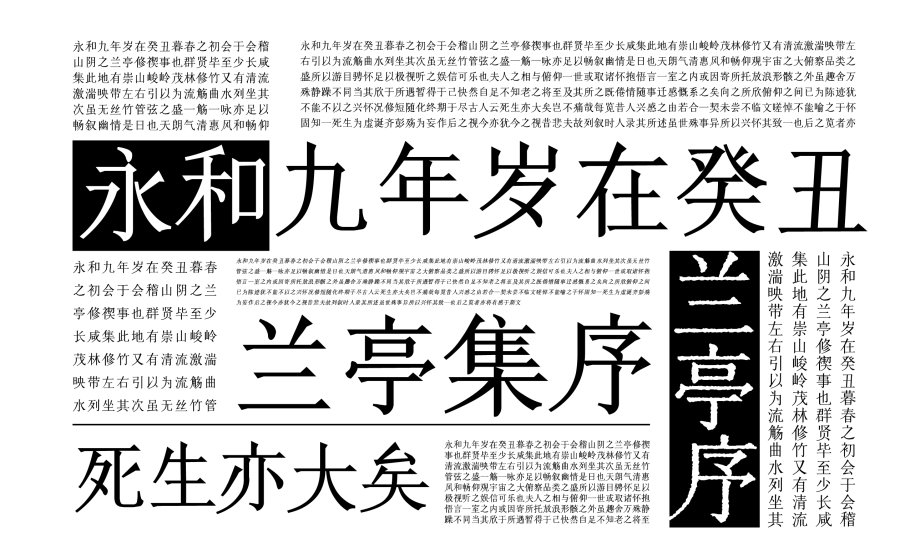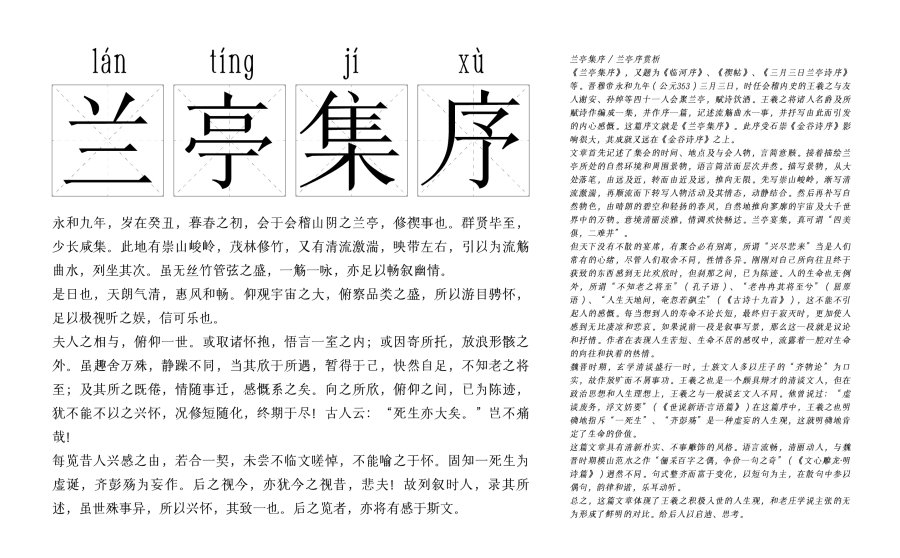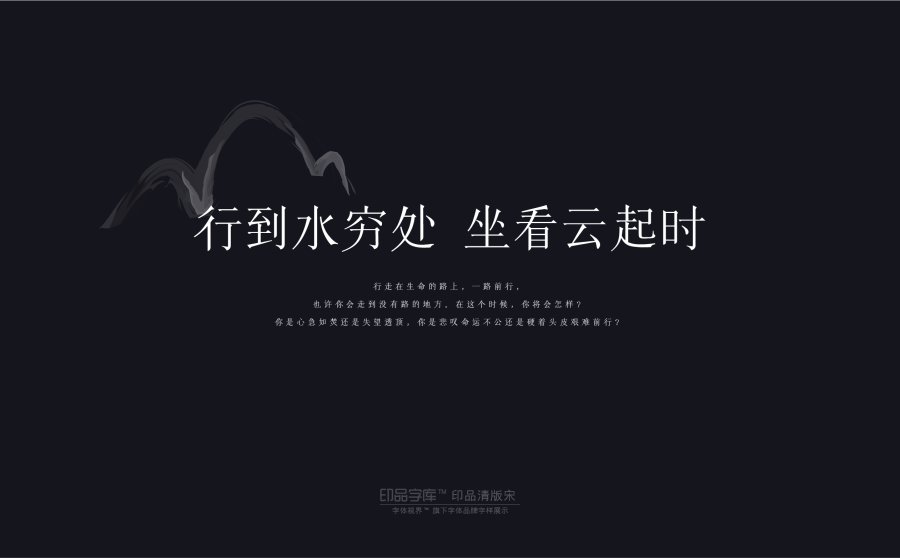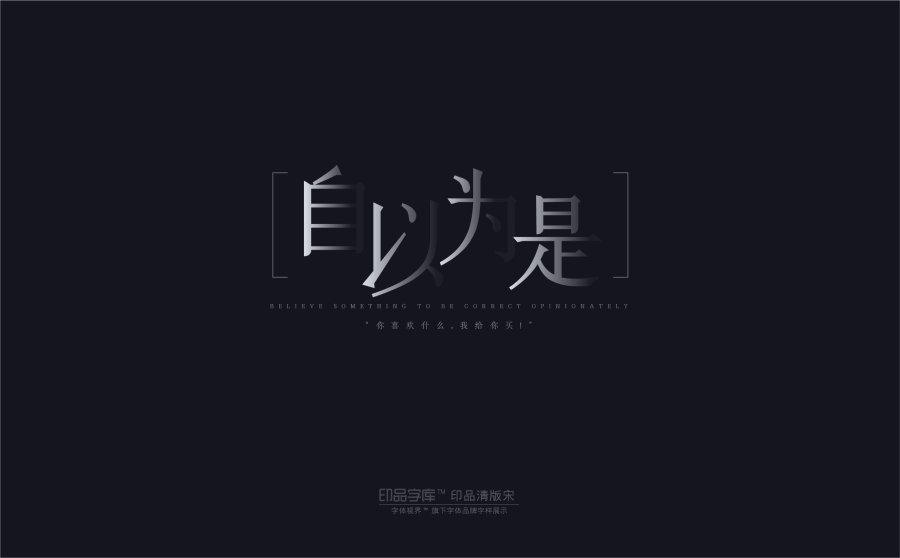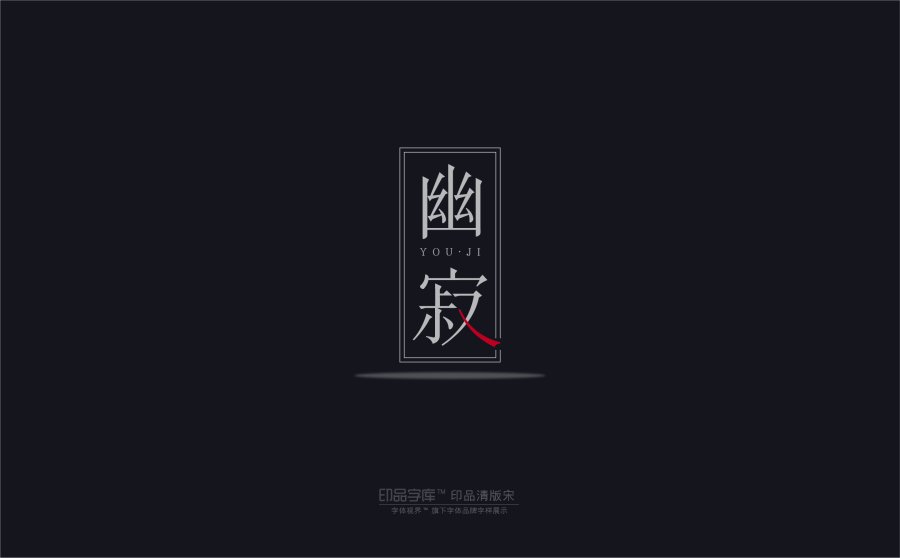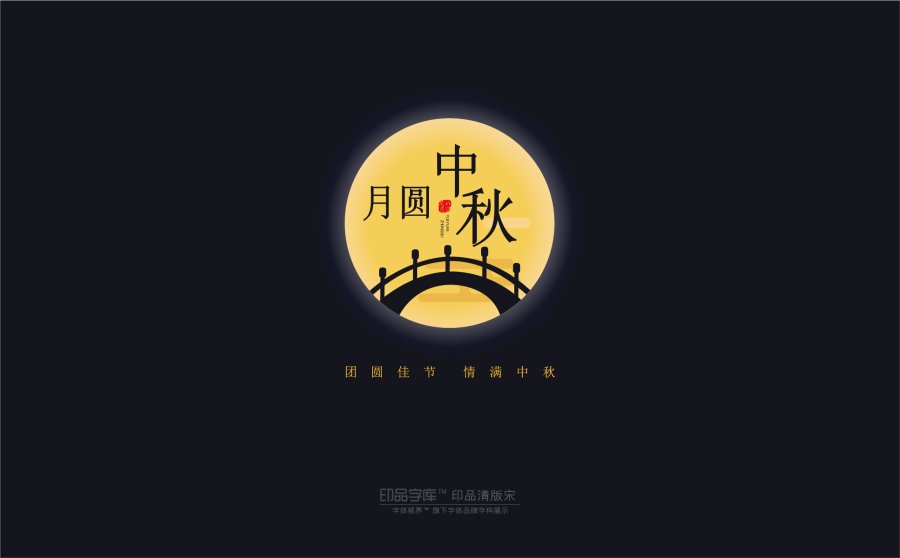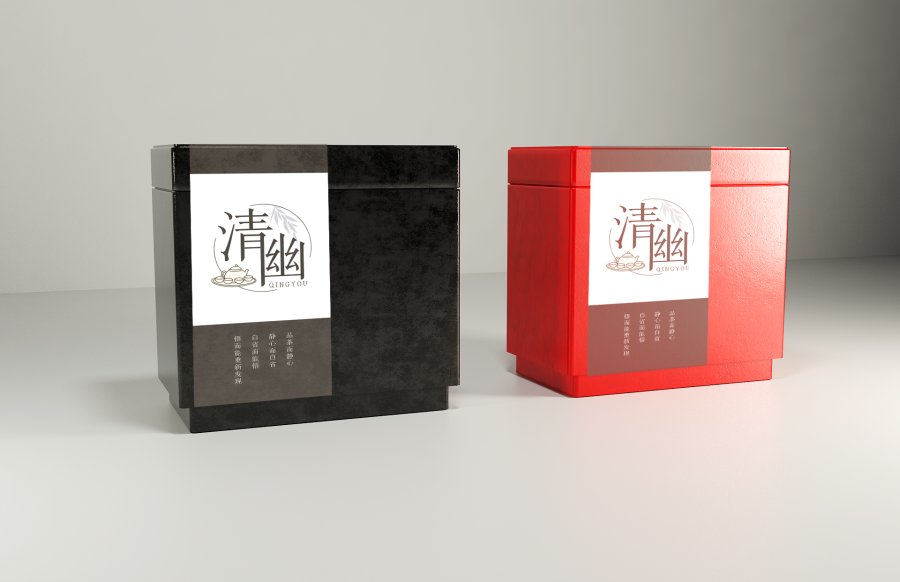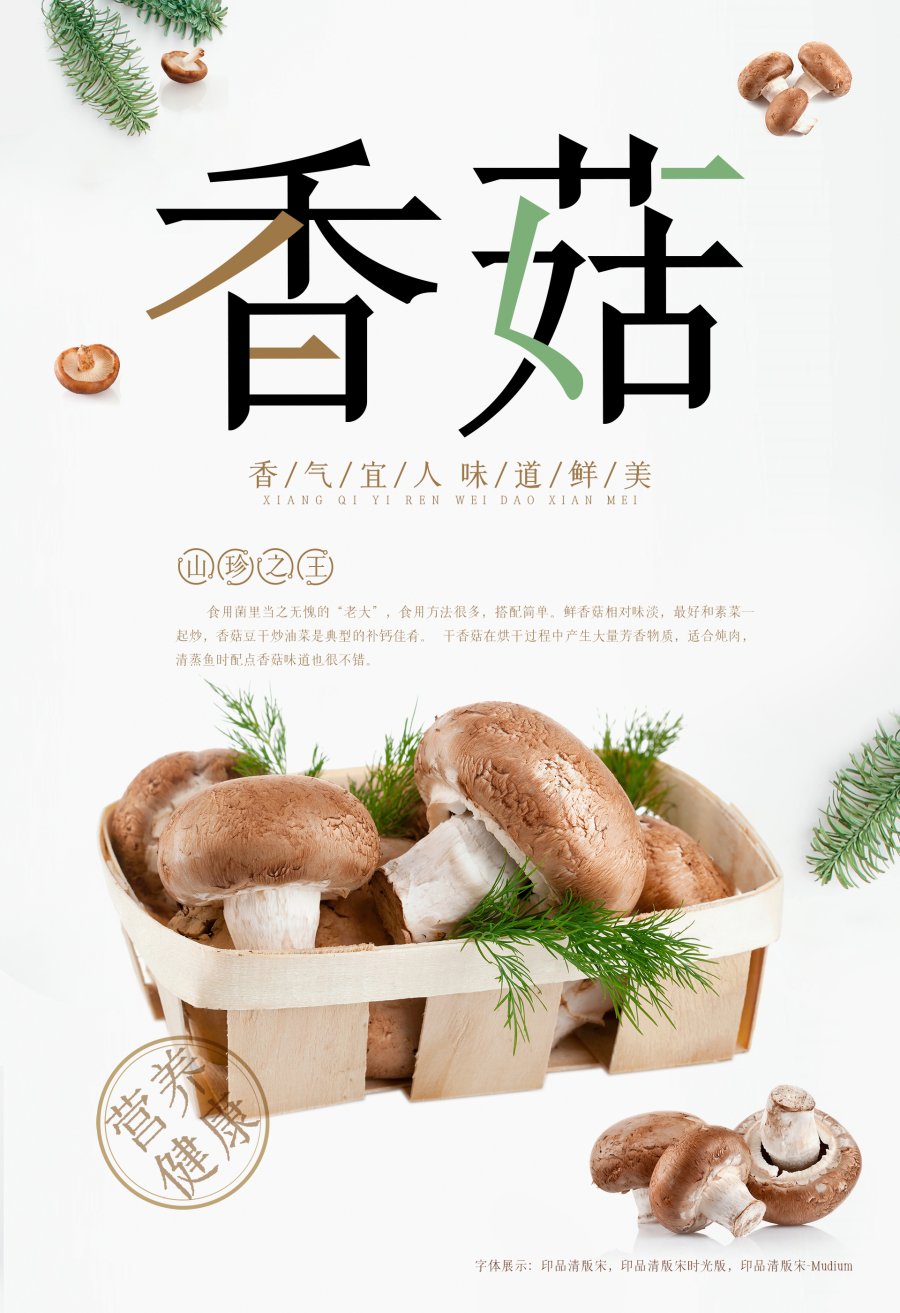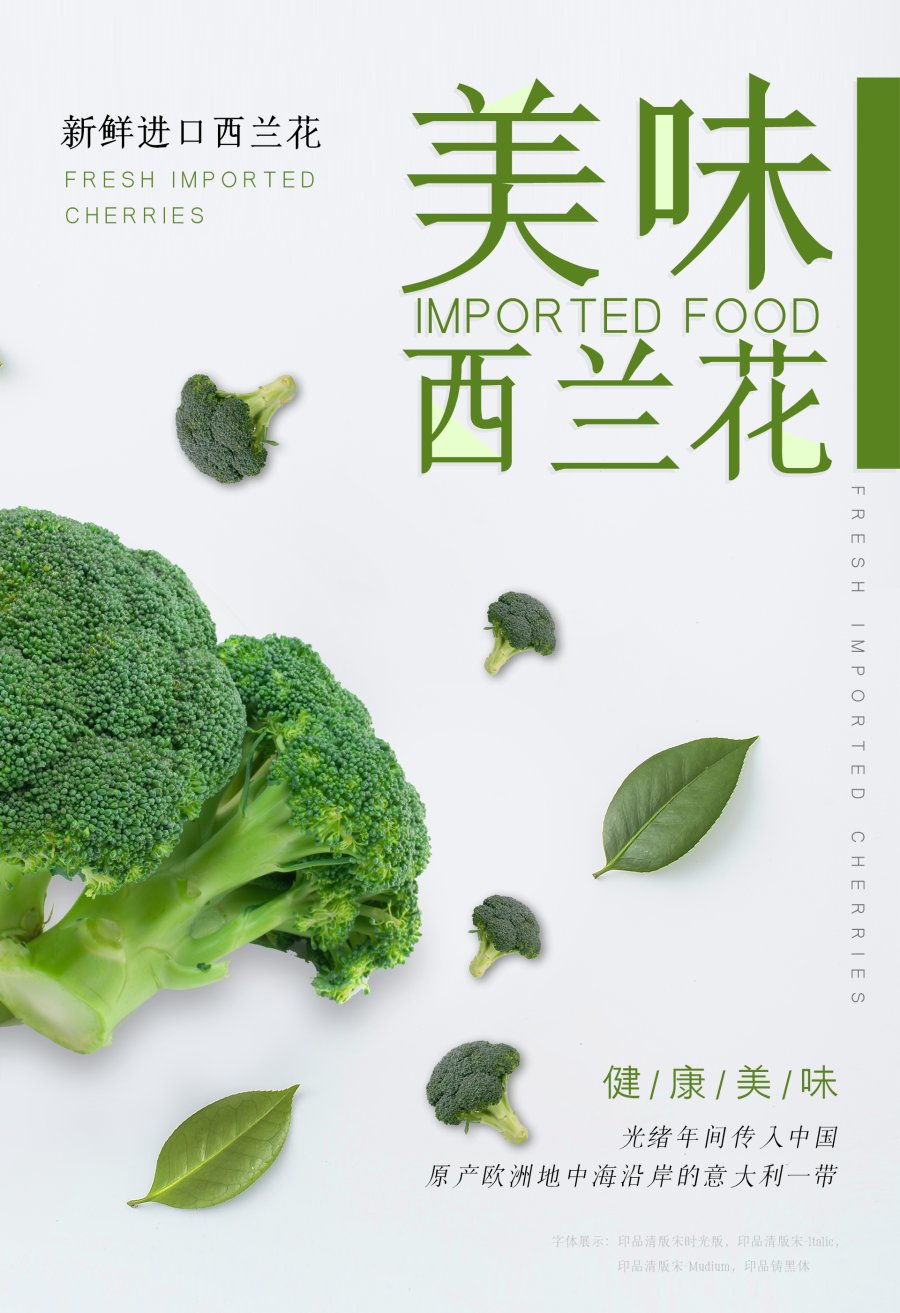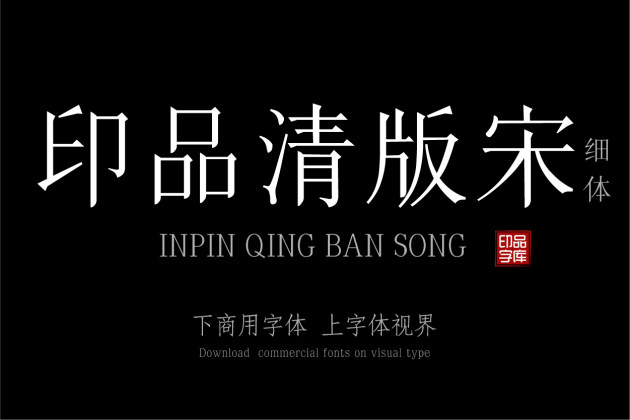
印品清版宋 细体
清版宋字体创作灵感源于清代康熙年间出版的《康熙字典》,结合清朝时期风格的宋体特点所创制的一款新宋体。字型修长、撇捺舒展、体态优雅,适合书籍与屏显阅读。
• 印品清版宋字体的创作灵感源于《康熙字典》。《康熙字典》是清朝康熙年间出版的图书,因此叫《康熙字典》,共收录汉字四万七千零三十五个(47035个)。此书的版本非常多,印品清版宋的灵感来源则是《康熙字典》的武英殿版本。武英殿刻本大多数都是以长宋体刻印书籍,刻印精致,装订豪华。 设计师在创作前查阅了大量关于《康熙字典》的资料,里面有大量的繁体字。而现代字库则只需用到常规字体六千多字,设计师在设计、制作的过程中需要反复地研究字型与笔画,在创作印品清版宋的过程中,设计师既保留了《康熙字典》的本身风格,同时也融合了自己的设计理念与想法。在笔画上作了细节的处理,让印品清版宋整体风格看上去更加具有灵动秀雅之美。印品清版宋字型修长、撇捺舒展、体态优雅,适合书籍与屏显阅读。